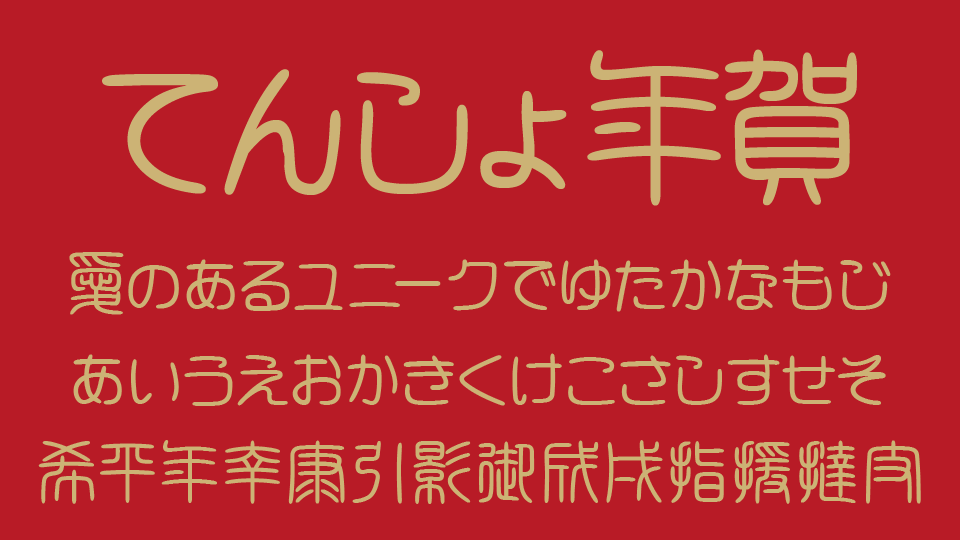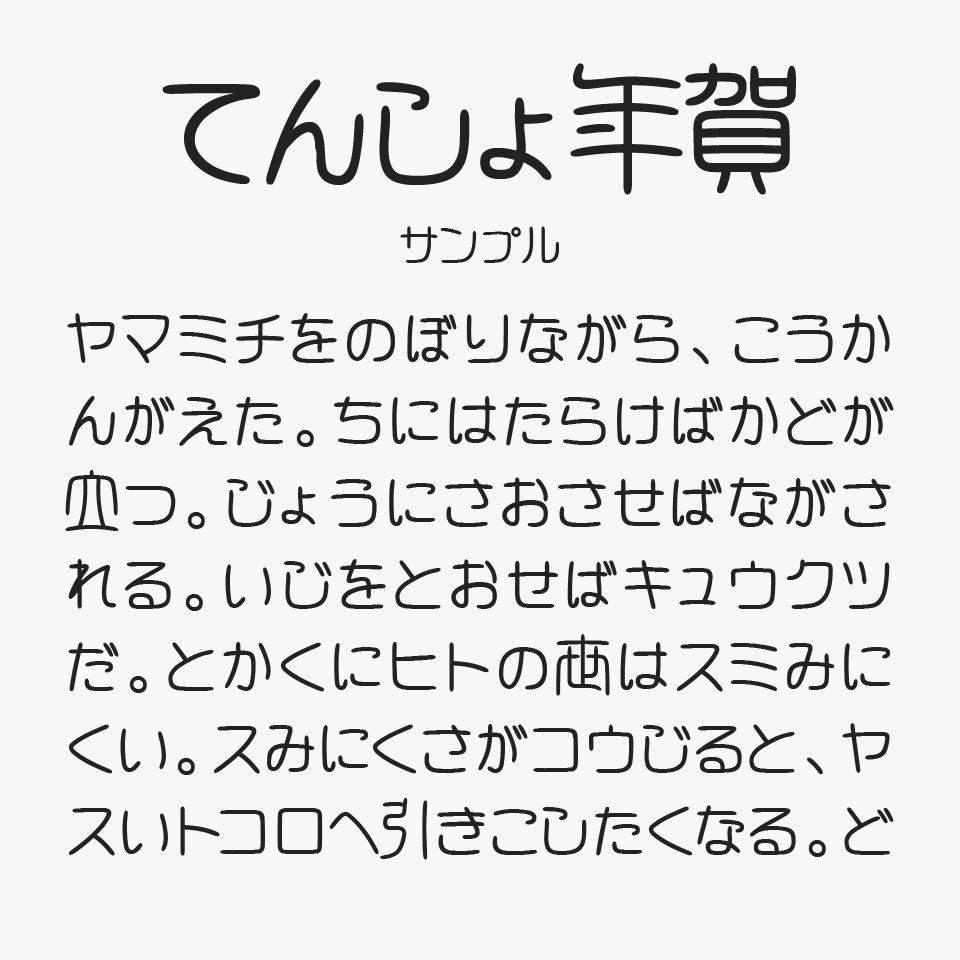
白舟篆書年賀
白舟篆書年賀フォントは、読みやすい手書き文字をベースに、篆書を思わせる丸みのある線や独特の字形を取り入れた篆書フォントです。
やわらかい手書き感のなかに、どこか古風で趣のある表情が自然に混ざり合い、一般的な手書きフォントとはひと味違った個性が感じられるデザインです。
線はやわらかく親しみやすいため、篆書の雰囲気を残しながらも難しい印象にならず、和風のデザインにも取り入れやすいフォントです。
年賀状での使用を目的に制作されており、新年のあいさつに使いやすい漢字が収録されています。年賀状はもちろん、お正月の販促物や和風のタイトル、季節のあいさつ、メッセージカードなどにもぴったりです。篆書らしい個性的な字形と手書きならではの温もりをほどよく楽しめる、使い勝手のよいフォントです。
収録文字は、漢字・ひらがな・カタカナ・数字・記号が収録されています。